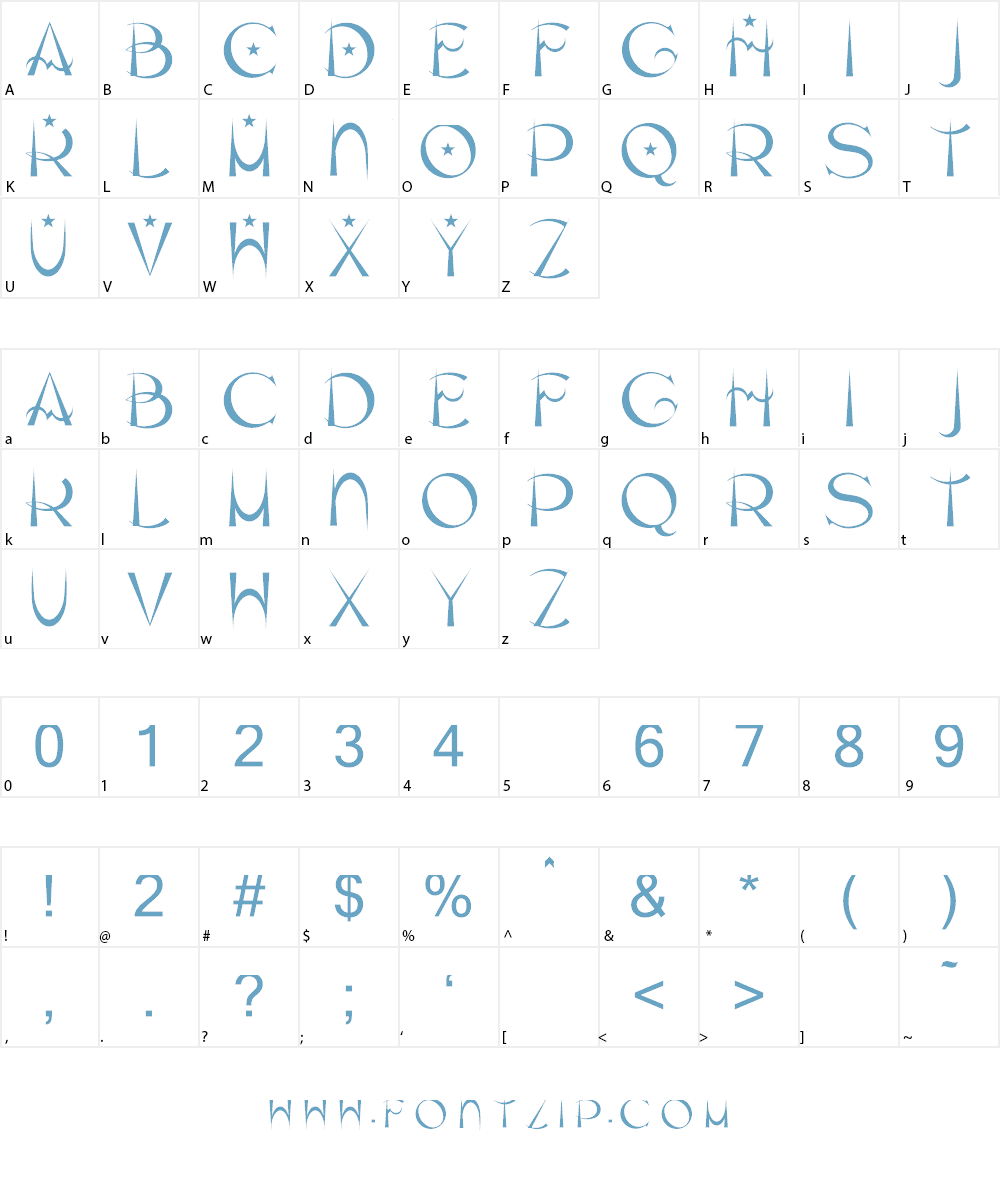
Série Paulistana – Pesquisa sobre a tipografia na arquitetura da cidade de São Paulo (Brasil).
Paulistana Series - Research about the typography in the architecture of the São Paulo city (Brazil).